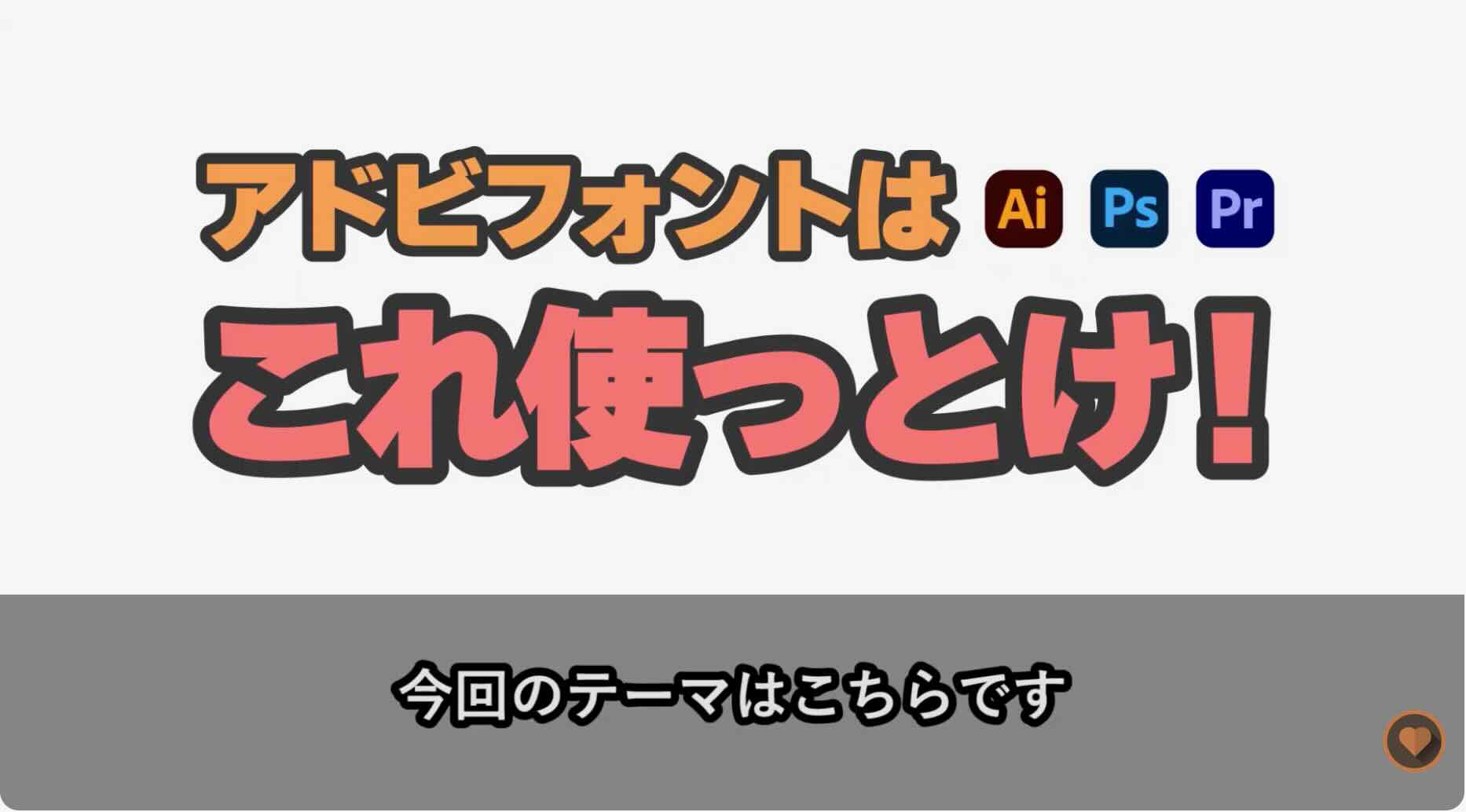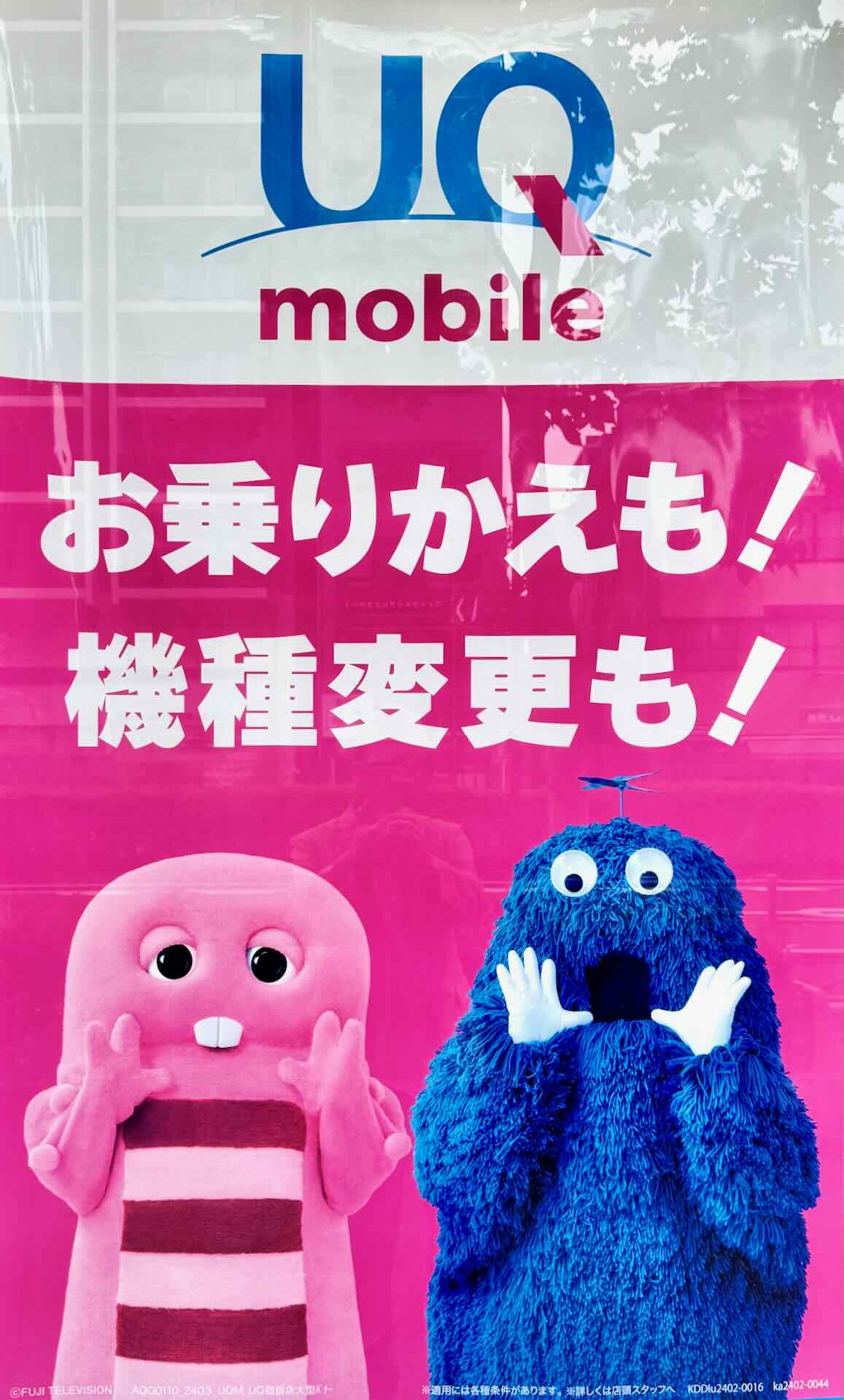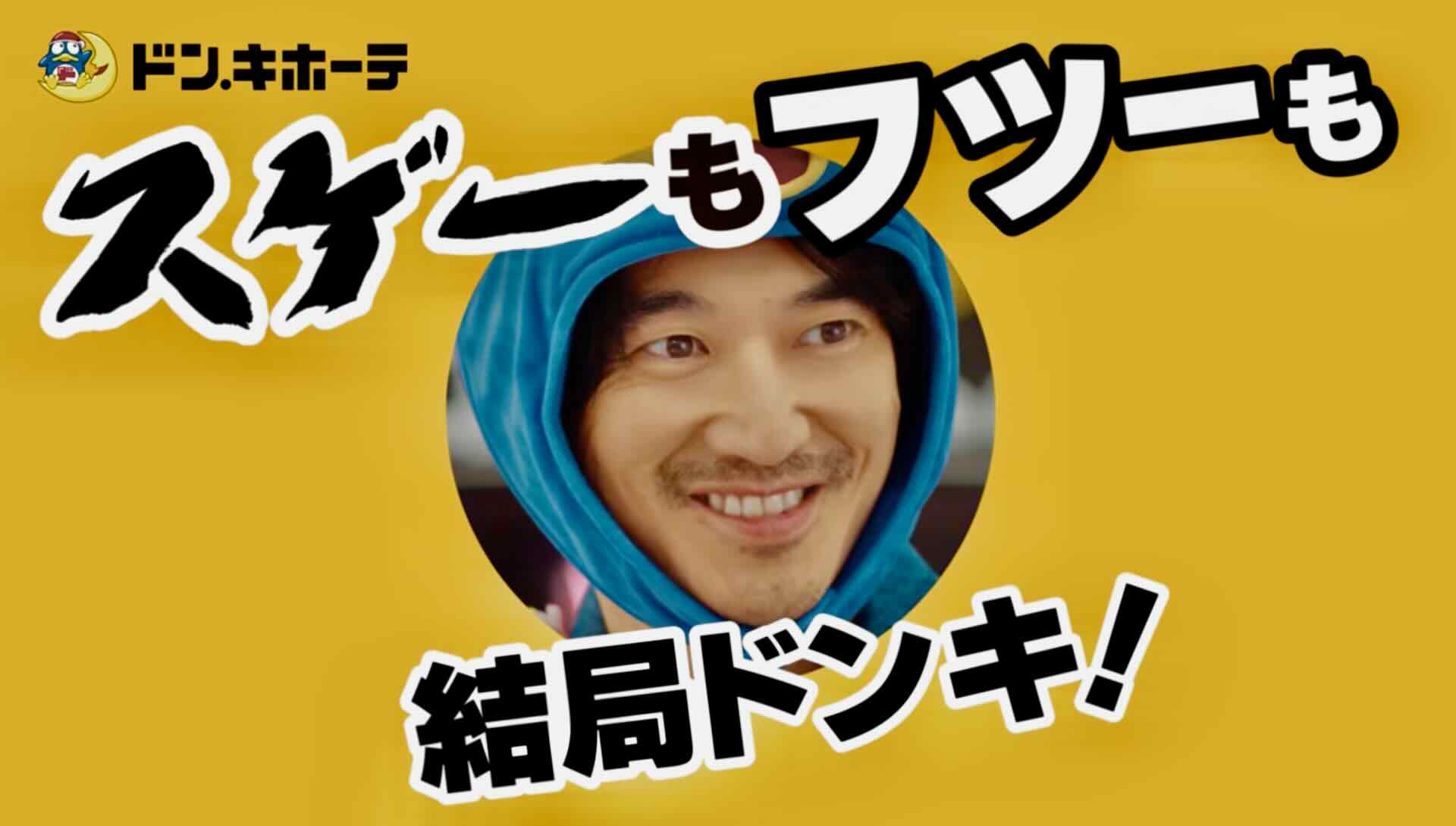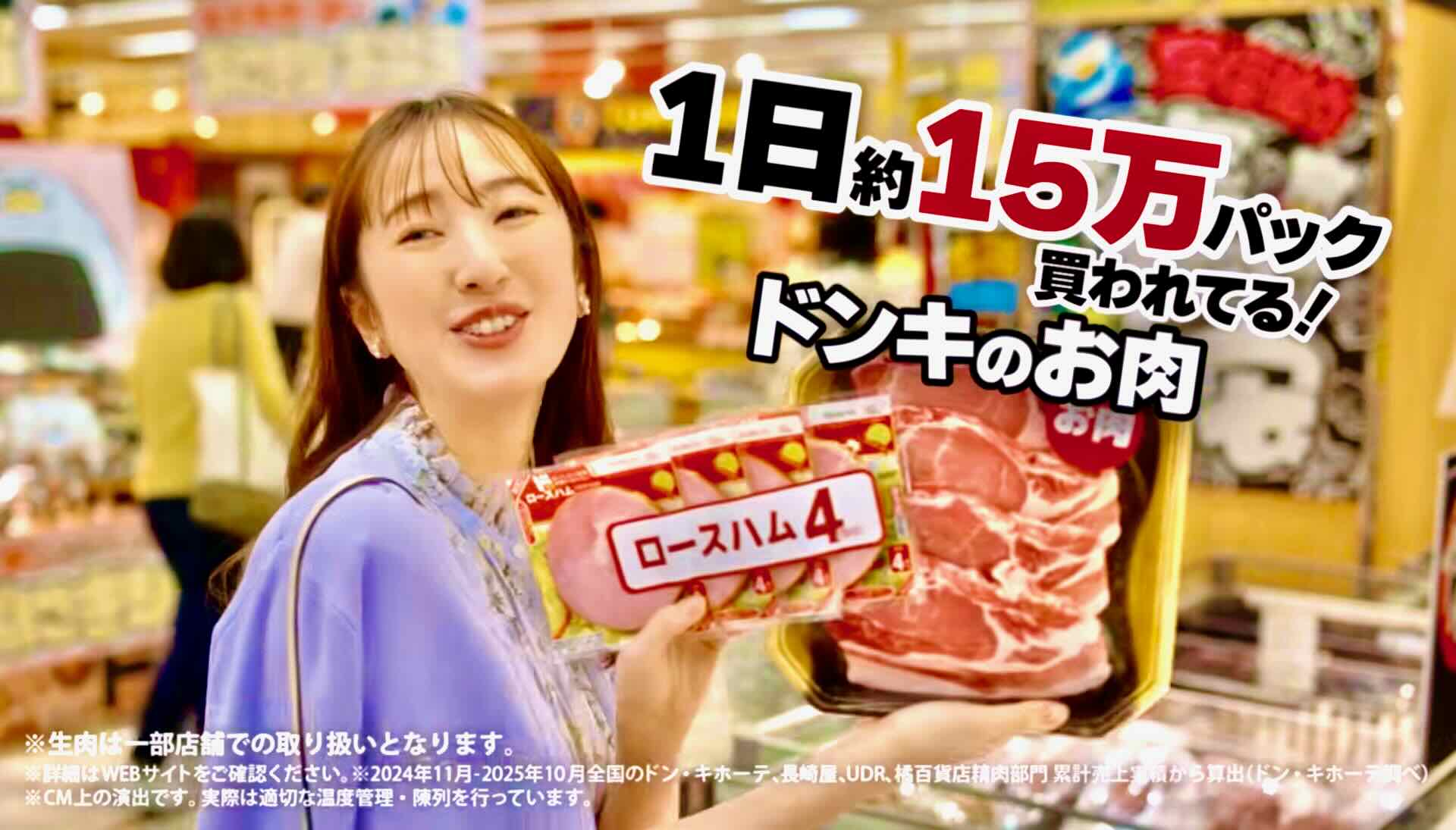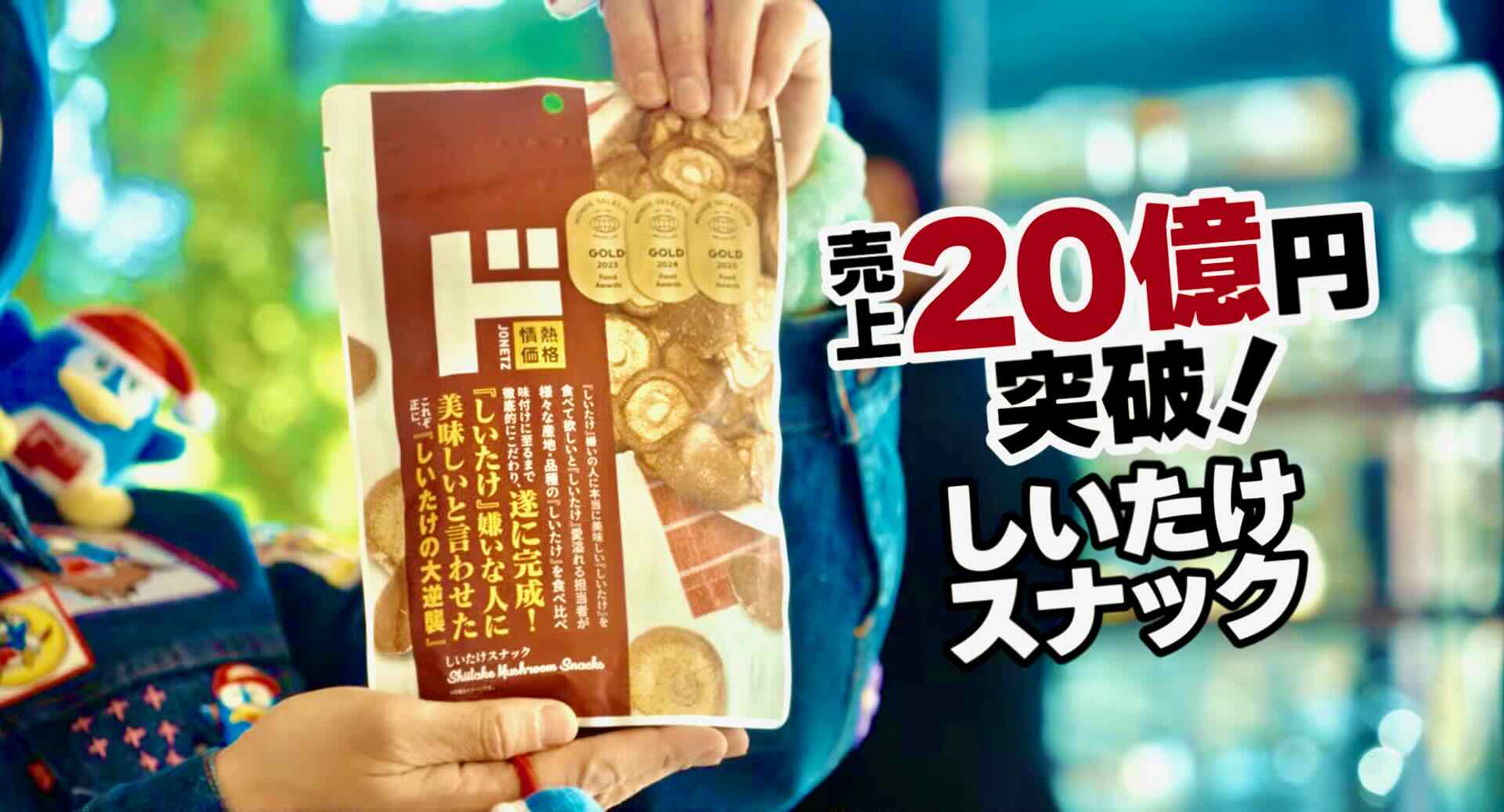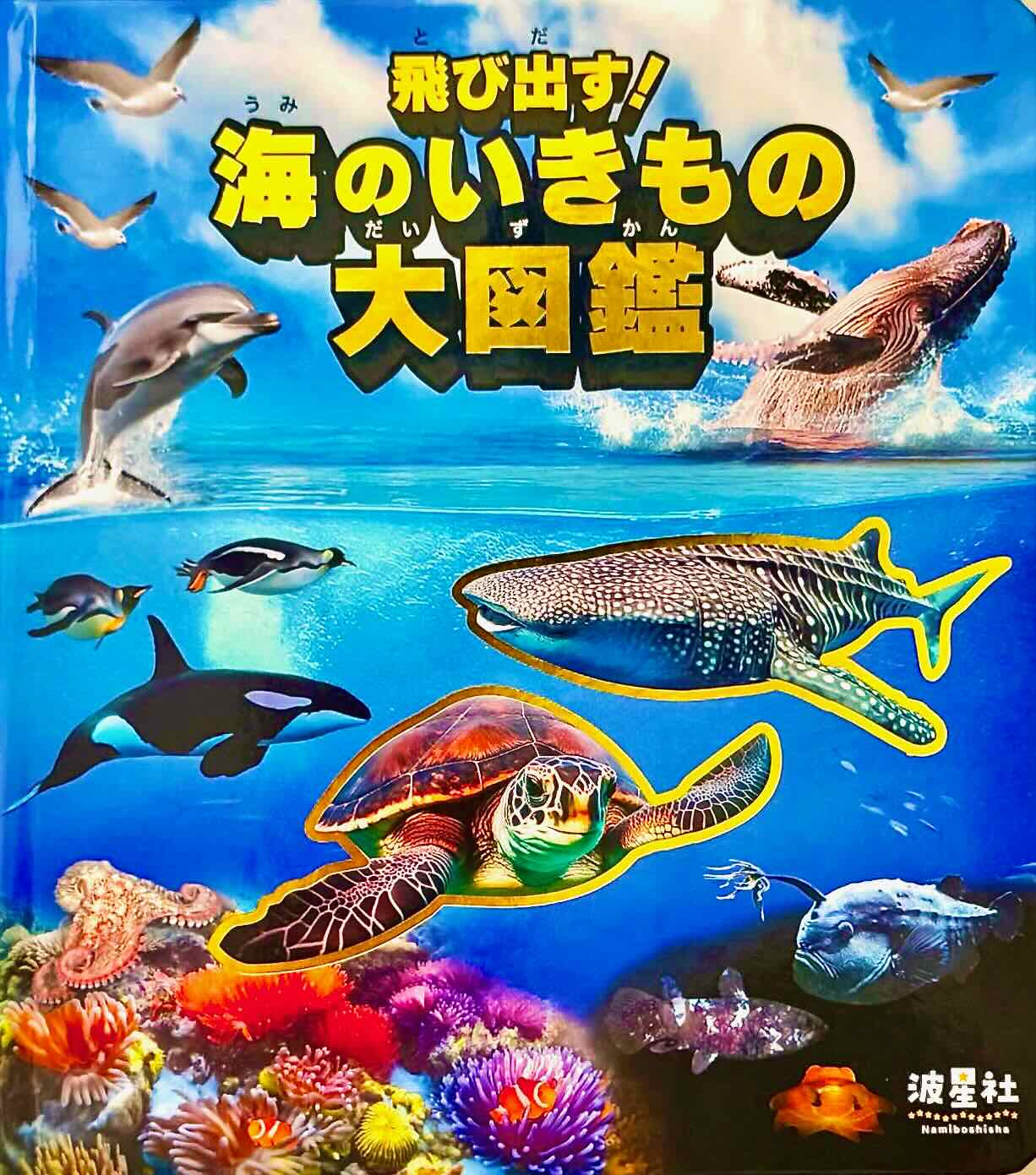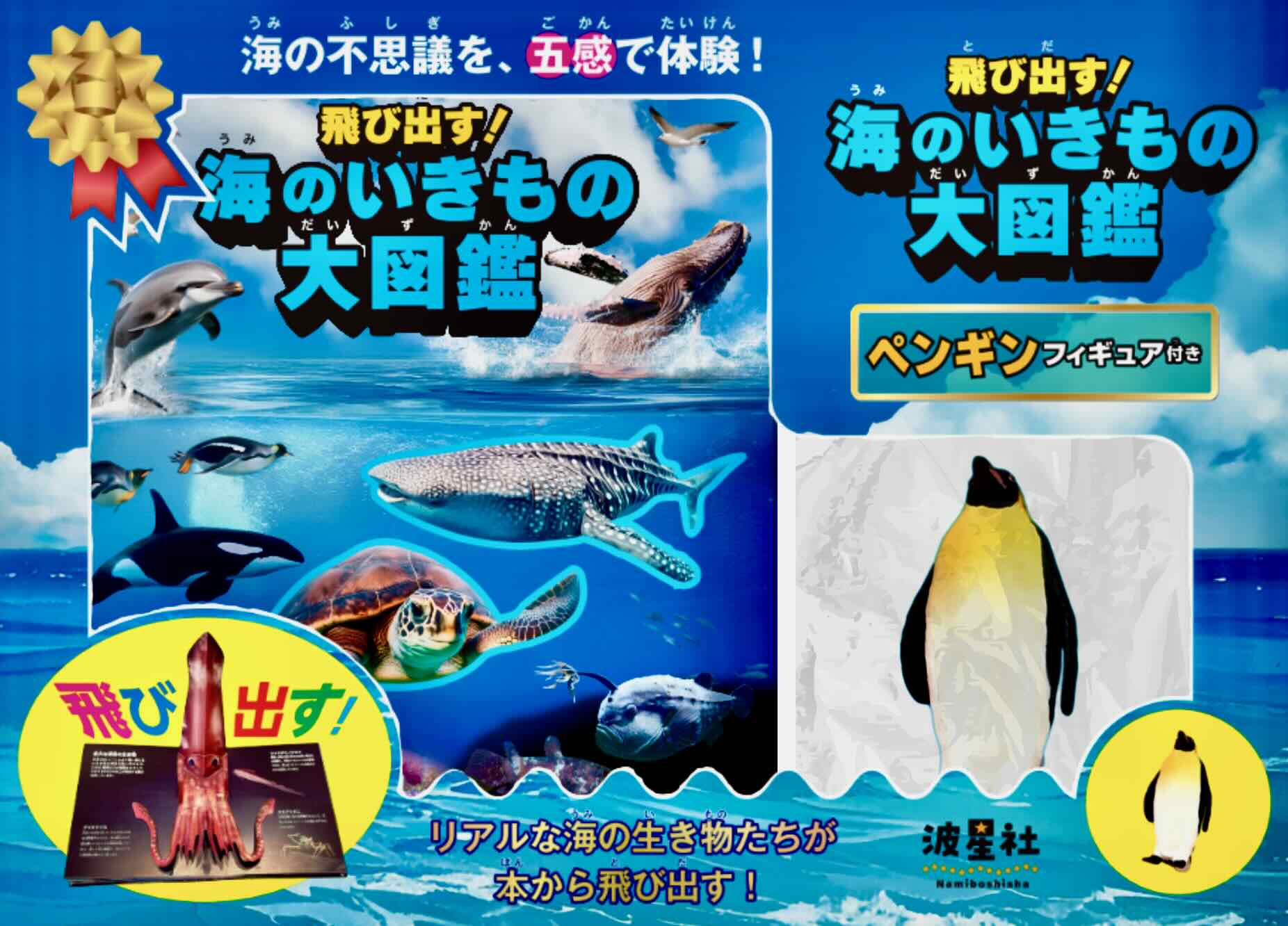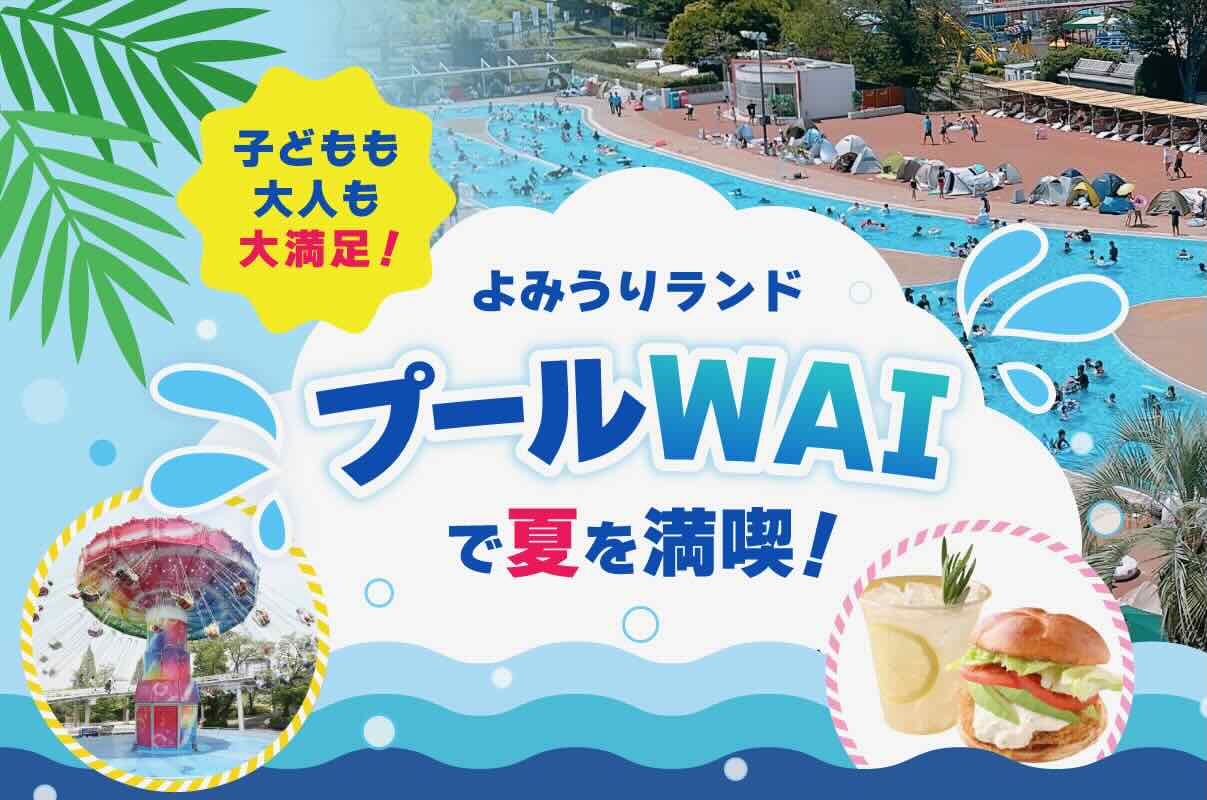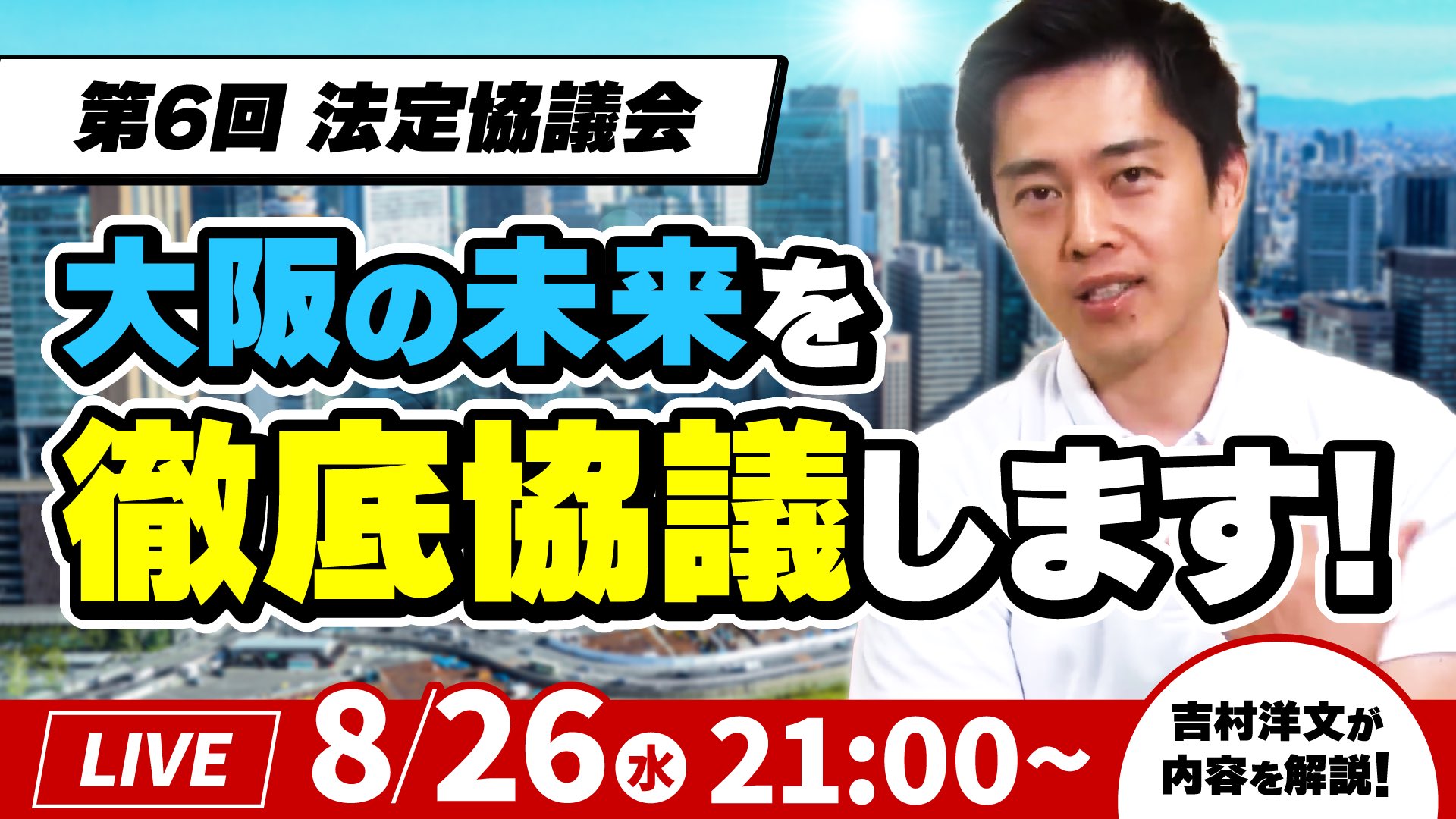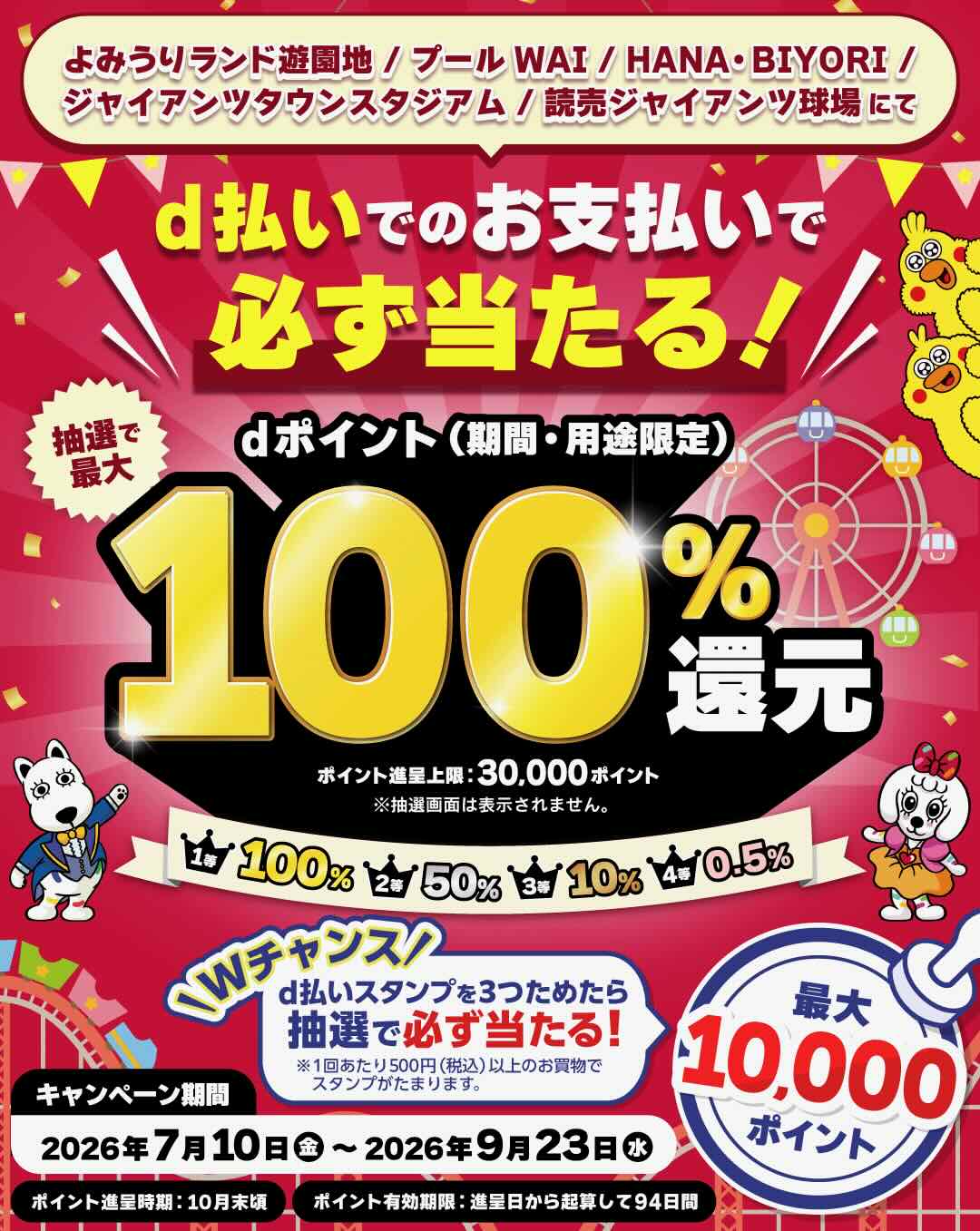
言べんの1画目 さとうゆたか
最近よく見かけるようになったルイカ系書体。
他の書体と、漢字で判別する方法がある。
それは、言べんの1画目が立っていること。
これは、ニタラゴルイカ。
これは、わんぱくルイカ。
「認」の文字。
これは、オリジナルのルイカ書体。
「信」の文字。
広告画像 さとうゆたか
松屋の広告。
英数字も見ておくれ〜。
これも。
まだある。
これもか。
追加…。
テレビ番組のサムネ さとうゆたか
ONE N' ONLYのフルアウトTV。
贅沢野菜 さとうゆたか
クノールの贅沢野菜スープ。
これも。
まだある。
もう1枚。
広告画像 さとうゆたか
よみうりランドの広告。
サムネイル画像 さとうゆたか
大阪都構想に関する法定協議会。
プールのポスター さとうゆたか
よみうりランドのプール。
「プールWAI」が、ルイカ書体(英字のIの形で判る)。
その上下の小さな文字は「わんぱくルイカ」書体。
本の表紙 さとうゆたか
書名:飛び出す!海のいきもの大図鑑
著者:なみぼし はなこ (企画・原案)
発行:波星社
これは、ポスターかな?
テレビCM さとうゆたか
ディスカウントストア「ドンキ」のCM。
これも。
もうひとつ。
ポスター さとうゆたか
携帯電話会社のポスター。
ショーウインドウの中に貼られていたものを、ガラス越しに撮った…。